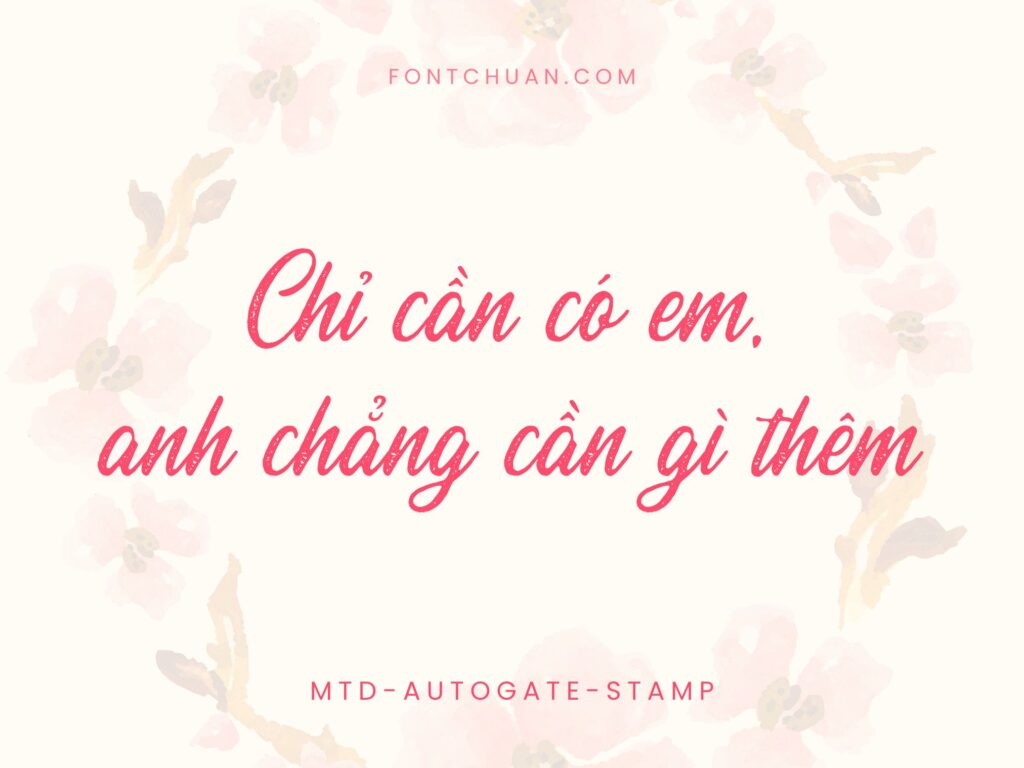
Font Autogate là một bộ đôi kiểu chữ độc đáo, bao gồm một font script viết tay và một font sans-serif, được thiết kế bởi Letterhend Studio. Với cảm hứng từ phong cách cổ điển, Autogate mang đến sự kết hợp hoàn hảo giữa sự mềm mại của chữ viết tay và sự mạnh mẽ của chữ sans-serif, tạo nên sự đa dạng và linh hoạt cho các thiết kế.
Phiên bản Autogate đã được Việt hóa bởi Mộc Hạ, hỗ trợ đầy đủ tiếng Việt cùng hơn 64 ngôn ngữ khác, mở rộng khả năng ứng dụng trong thiết kế đa ngôn ngữ. Font này đã được thành viên Font Chuẩn sưu tầm và chia sẻ, đáp ứng nhu cầu của cộng đồng thiết kế. Với thiết kế bao gồm các ký tự viết tay tinh tế, chữ sans-serif rõ ràng và các ký tự thay thế đa dạng, Autogate phù hợp cho các ứng dụng như thiết kế logo, thương hiệu, thiệp mời và các ấn phẩm quảng cáo. Các ngành nghề như quảng cáo, giáo dục, công nghệ và ẩm thực có thể tận dụng font này để tạo ra thiết kế ấn tượng và thu hút.